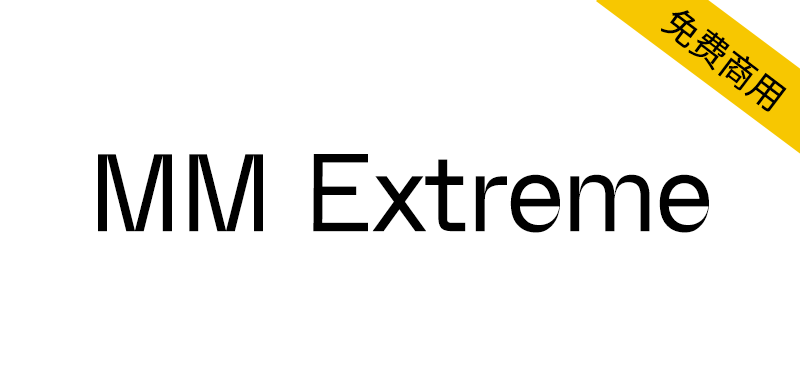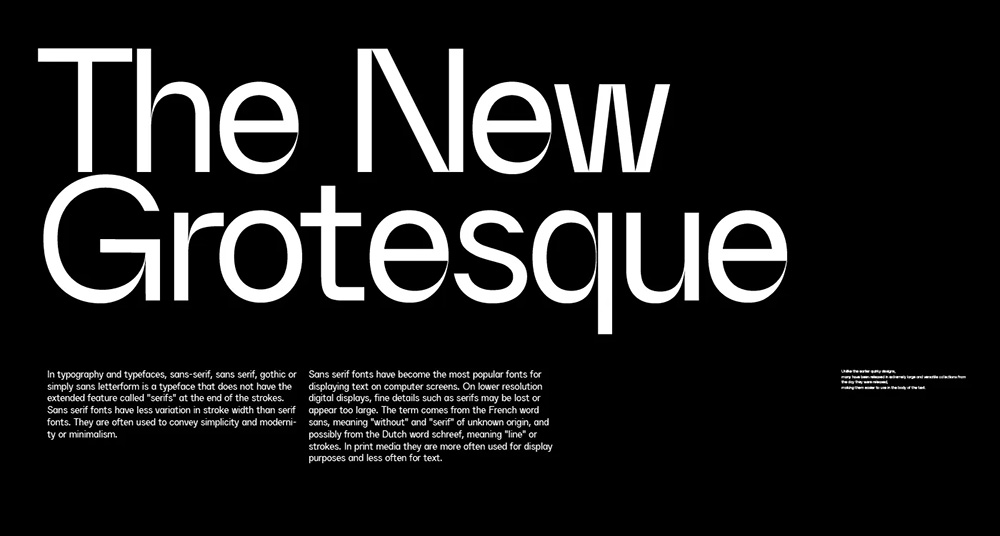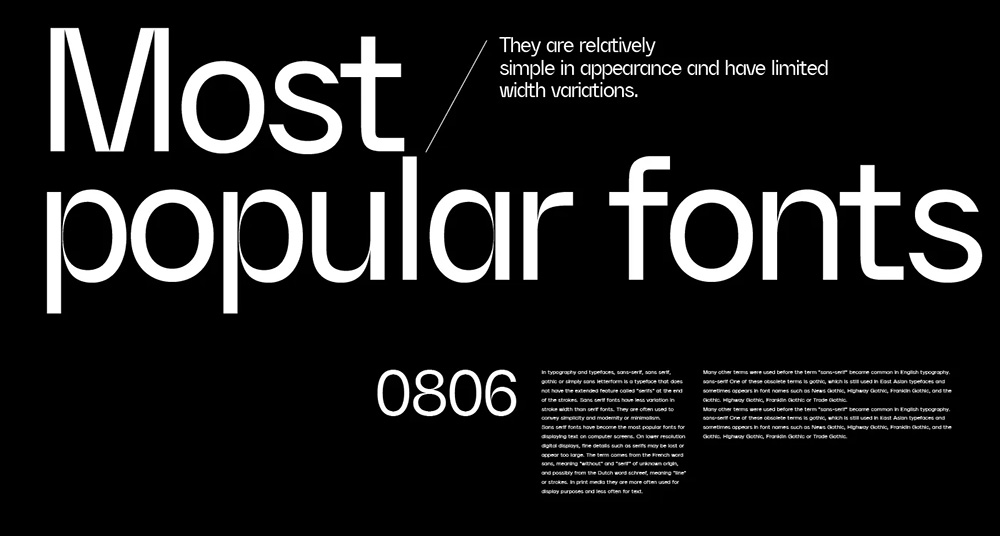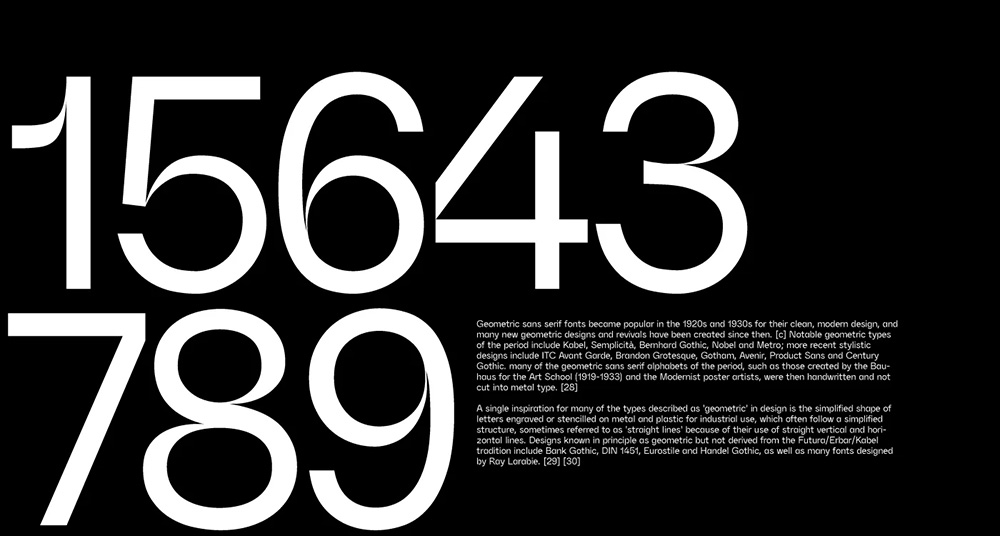
【MM Extreme】现代无衬线字体,适用正文或超大标题
MM Extreme是一款现代无衬线字体,采用扁平的形式和笔画分离的处理方式。大段文字的编排效果良好,用作大标题时则有锋利而夸张的笔触形态。字体放大后充满了错觉,这种奇特的风格为字体设计增添了风格。它可以用于正文布局,以及超大的标题。字符集标准:Adobe Latin ;字符集数量:229(个)。
【MM Extreme】现代无衬线字体,适用正文或超大标题